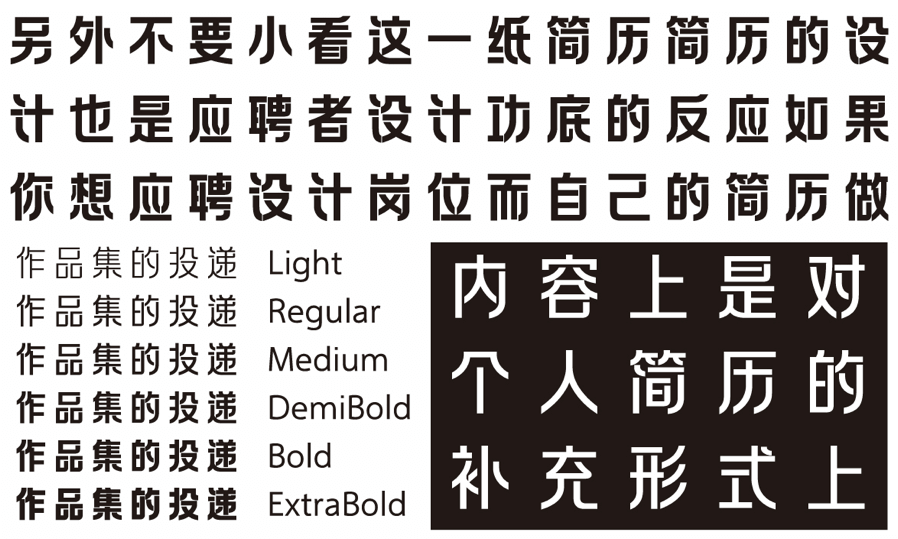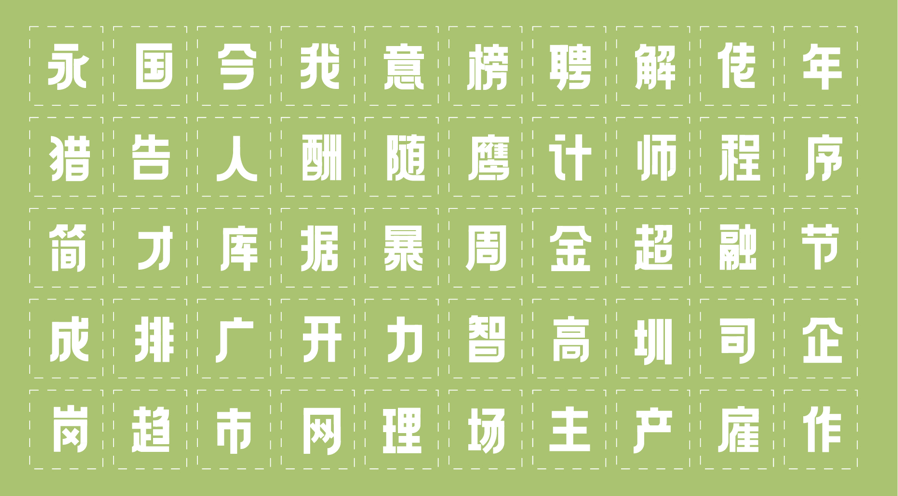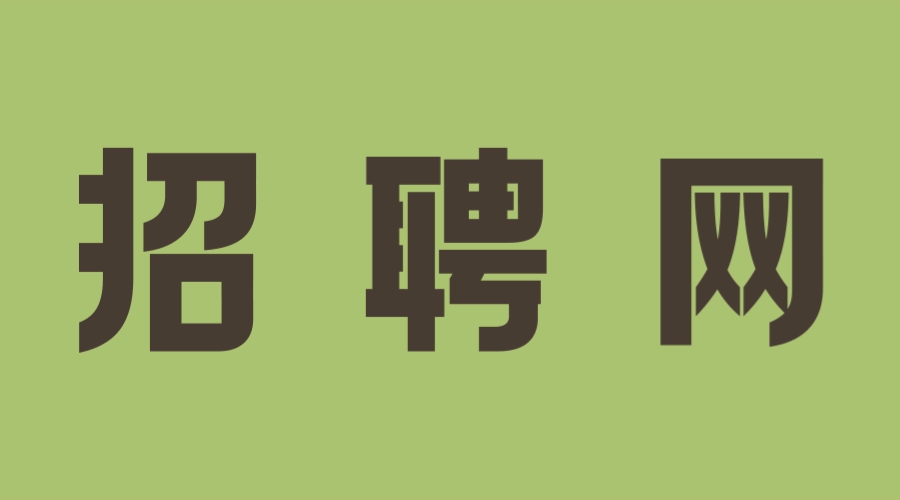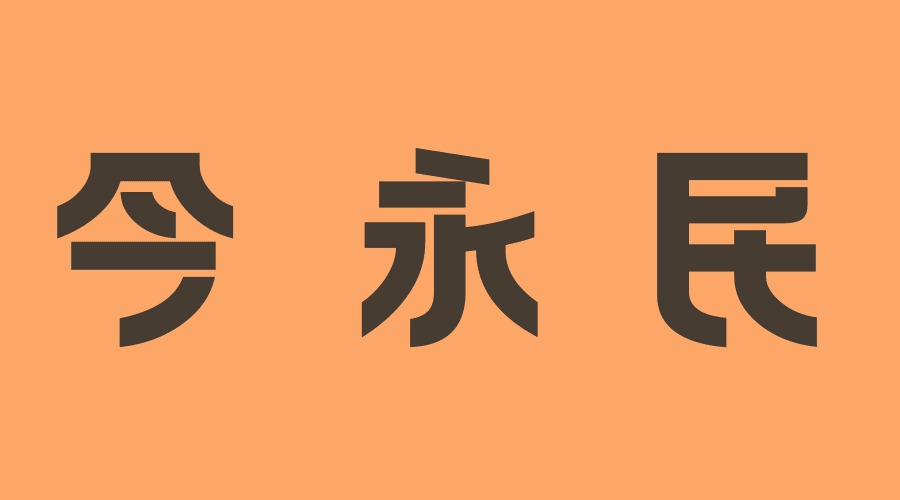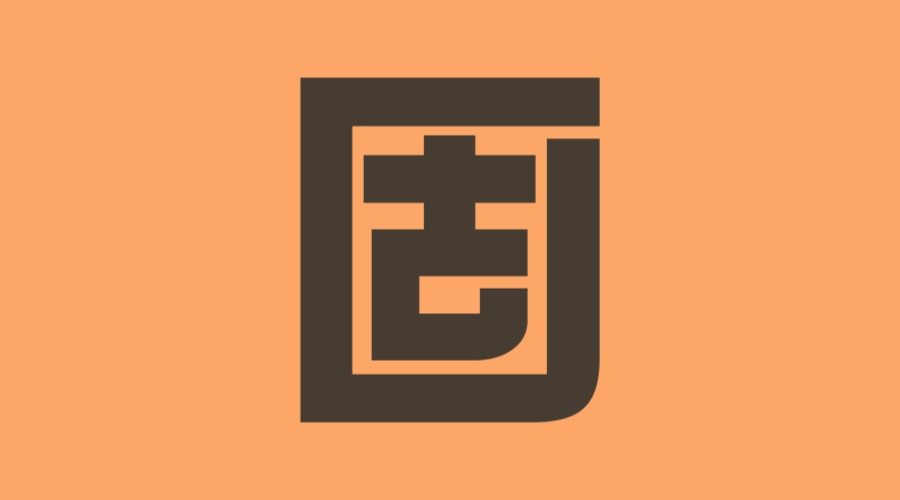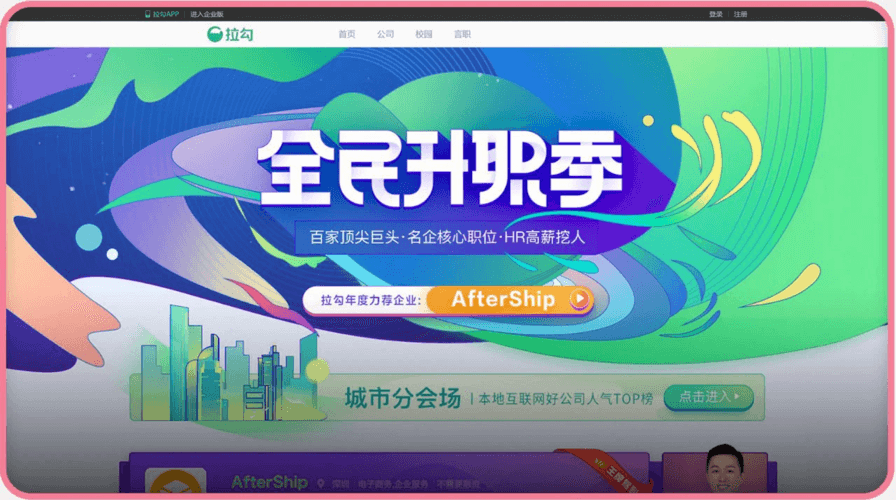
方正拉勾标题体
2018年,互联网招聘平台拉勾网推出线上招聘活动“全民升职季”,为强化该活动的记忆点、打造个性化品牌形象,拉勾网从重要视觉元素——字体入手,通过打造一套活动专用标准字体,来实现品牌的视觉营销。
为了延伸字体价值,赋予其更久远的生命力,拉勾网与方正字库达成合作,以此活动字体为创意基础,开发出一款适用性更广的现代创意字体。最终,方正合作设计师郭炳权先生带领团队完成其产品化,方正拉勾标题体正式面世。
方正拉勾标题体是一款针对互联网活动、广告、报刊等媒介而设计的现代创意字体,其字形整体偏矩形化,重心较高,字体端正清朗、气质统一。
方正拉勾标题体在黑体的基础上融入了民国美术字的特点,笔画连接处适当的缺口处理,既保留了旧式印刷广告体的韵味,又注入了新时代的活力;合理的笔画避让使得字体醒目易读,更具识别性。
这款字体笔画粗细均匀,撇、捺整体呈镜像对称,笔画转折采用“外圆内方”的设计,内部折角方直,风格果敢;外部的拐角处则进行了导圆处理,线条圆滑,字形整体更具美感和丰富性。
拉勾体实际应用场景